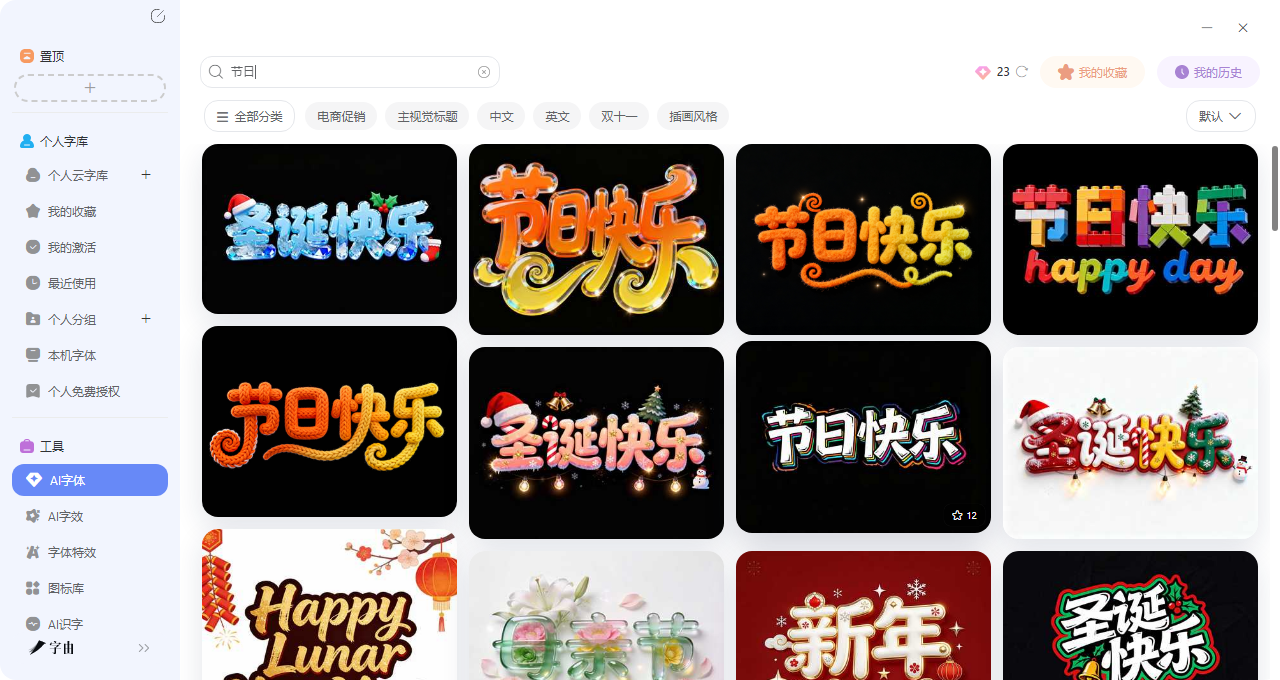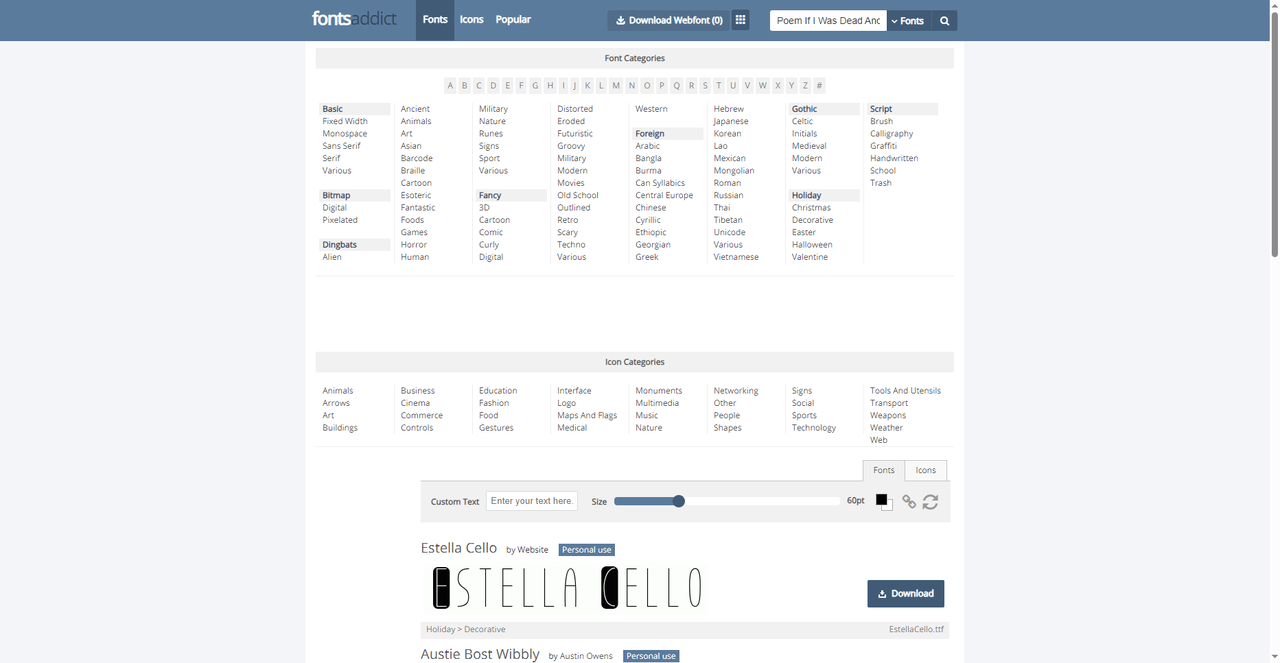
不会设计也能做节日字?这5个工具能帮你一键搞定
一年中的节日实在是不少,春节、情人节、万圣节、圣诞节……一年到头,总有那么几个日子,需要我们亲手做一些有节日氛围的东西。比如说给朋友发一张贺卡,又或者是帮公司做节日祝福海报,那么这时候往往缺少的不是创意,而是一款合适的字体,这时候派上用场的就是节日主题字体设计工具了,输入文字就能一键生成,根本不需要你会PS。在下面的内容里我会介绍了5 个实用的节日主题字体设计工具,能在短时间内帮你快速做出有节日感的文字,需要的可以收藏了!
针对上面的问题,字由的AI字体功能,就是专门用来解决这个问题的。你不用自己琢磨怎么调出雪花装饰,也不用研究怎么把“新年快乐”四个字做出烫金效果。打开客户端,在AI字体里搜一下“圣诞”或“春节”,现成的模板就摆在你的面前了。那么下面我会教大家具体的步骤:
第一步:在客户端或者是网页版进入AI字体页面后,在搜索框里输入“春节”“圣诞”“情人节”“万圣节”等关键词,系统会自动筛选出所有带节日氛围的模板。你也可以直接点进一些专有标签进去挑选,想做圣诞主题,就搜“圣诞”或“Christmas”,如果今年流行某个具体风格,比如“国潮春节”,也可以直接搜关键词
第二步:搜索结果会展示各种风格的预览图,每个模板都有独特的设计:
- 圣诞风:红绿配色、雪花装饰、圣诞帽元素、松枝环绕、圣诞袜点缀,适合做圣诞贺卡和朋友圈封面。
- 春节风:大红底色、金色描边、祥云纹样、灯笼装饰、倒福字样。
- 情人节风:粉色系、爱心图案、浪漫花体、玫瑰花瓣、光晕效果,温柔又有仪式感。
总之每个节日都会有对应的模板,你可以点进去试试看,还可以看到更多细节。
第三步:点击选中的模板,进入编辑页面。在输入框里填你想生成的文字,比如“新年快乐”“Merry Christmas”“情人节快乐”“万圣节狂欢”。需要注意的是每个模板的字最好不要超过6 个,这也是为了画面效果好,如果字数不一致,AI也会尽量适配,但可能会有些偏差,所以建议按模板字数来。
第四步:确认文案后,点“立即生成”,等20-30秒左右就能拿到图。
所以,有了字由以后你就不用再对着空白画布发呆了,只要打开字由,搜个节日,选个模板,填上祝福语,几十秒就能拿到一张有氛围的节日字。
2、Fontsaddict
Fontsaddict 的分类十分细致,在“Font Categories”里,有专门的“Holiday > Decorative”分类。从主页看,里面有不少节日相关的装饰字体:
- Estella Cello:免费个人使用,适合节日装饰
- Austie Bost Wibbly:可爱手写体,适合儿童节日
- Print Oldyz:复古印刷风格,适合怀旧节日
- Love Me Tender:免费软件,情人节主题
而且这个网站还支持自定义预览文本,你可以输入自己的节日祝福语,实时看效果。每款字体都标注了授权类型(个人使用、免费软件、共享软件等),下载前看清说明就行。
3、Fonts101
在这个网站里字体的总数量是十分可观的,总体上收录了超过4万款免费字体,它的搜索功能非常强大。在搜索框里输入“holiday”或“christmas”,就能找到大量的圣诞节字体。当然其他的节日字体也包括在内,每个字体都有下载次数(如3.7k views、2.5k views),可以判断受欢迎程度。网站还提供每日免费字体邮件订阅。
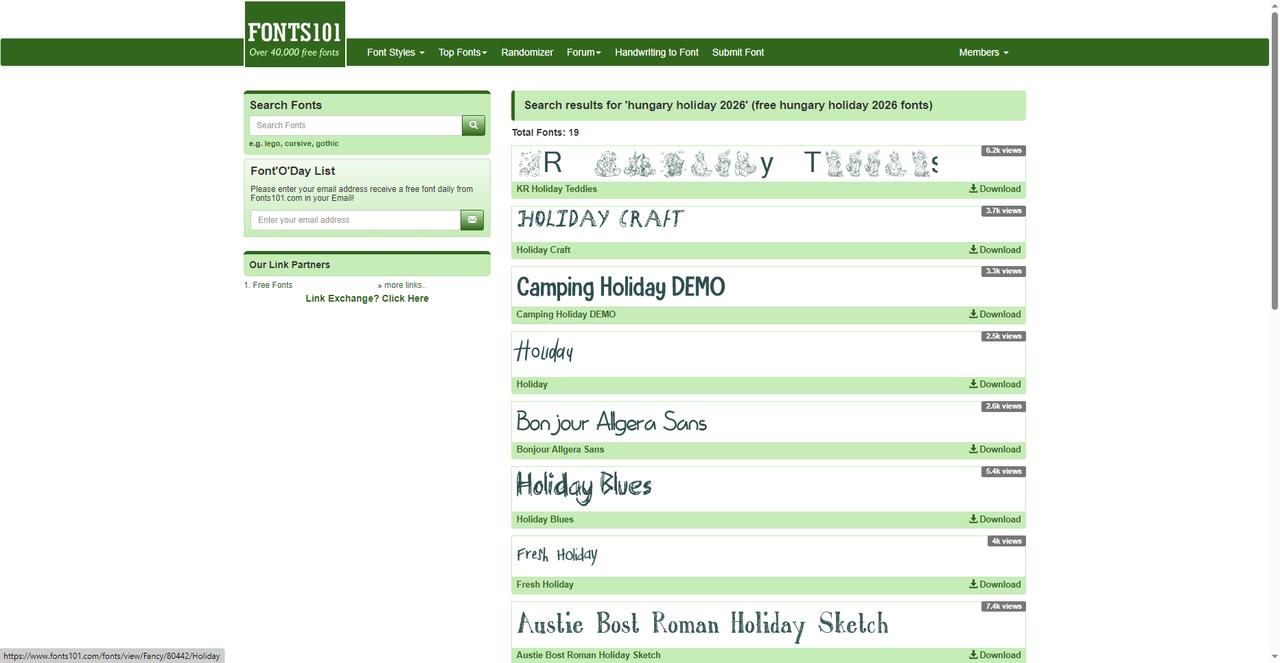
4、50 Best Free Holiday Fonts
在这个网站里精选了50 款免费节日字体,全部来自Google Fonts 或系统安全字体,完全免费可商用,无需版权标注。每款字体都有详细预览和说明,你可以输入自己的文本,实时预览效果。每款字体都提供了下载链接,直接跳转到Google Fonts。下面是几款字体推荐:
- Mountains of Christmas:欢快的手绘风格,适合圣诞节贺卡和祝福。分类为“display”,人气774,趋势1207。
- Pacifico:流畅的刷笔字体,温暖亲切,像手写的节日祝福。分类“handwriting”,人气107,趋势1609。
- Great Vibes:优雅流畅的草书,适合浪漫情人节或正式节日邀请函。
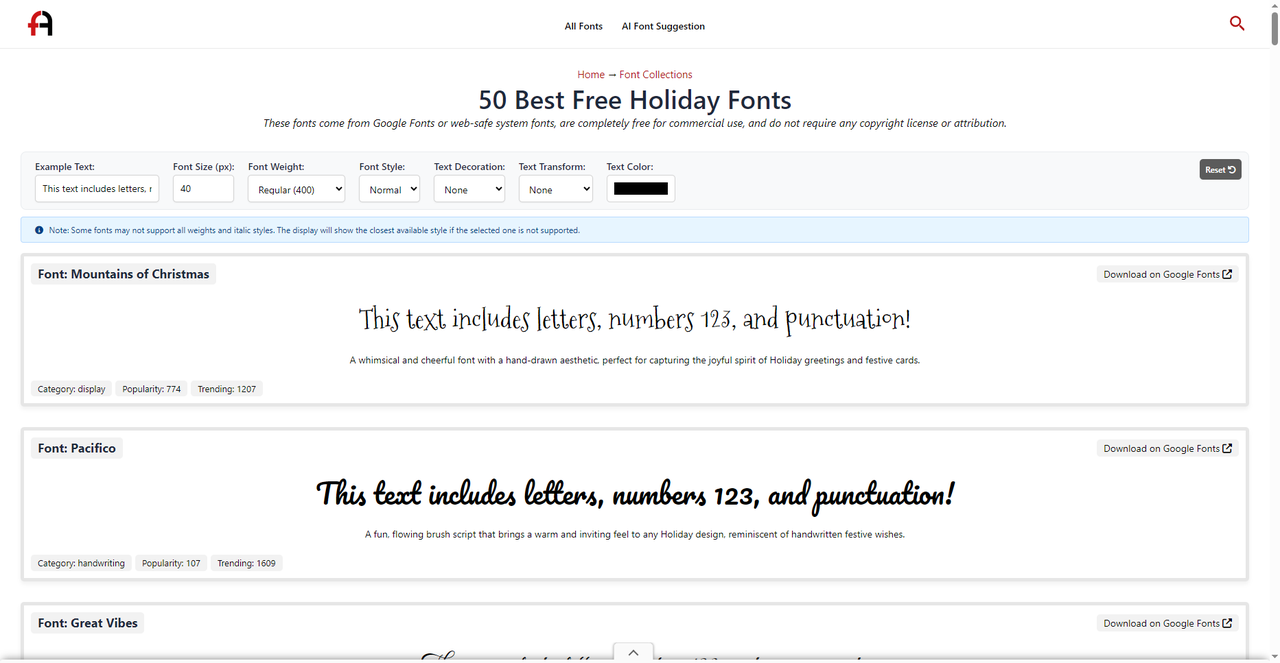
5、Fontspace
这也是我经常提到的一款字体网站,它有一个专门的“Holiday Fonts”分类,涵盖了各种节日的字体。据我所知,相关风格标签包括:Cursive、Fancy、Script、Handwriting、Cute、Modern、Bold、Fun、Christmas、Logo。每款字体都有下载次数(如185.7k downloads)和用户评分,可以帮你快速判断字体的受欢迎程度。Fontspace还支持在线预览,输入你的节日祝福语,实时看效果。